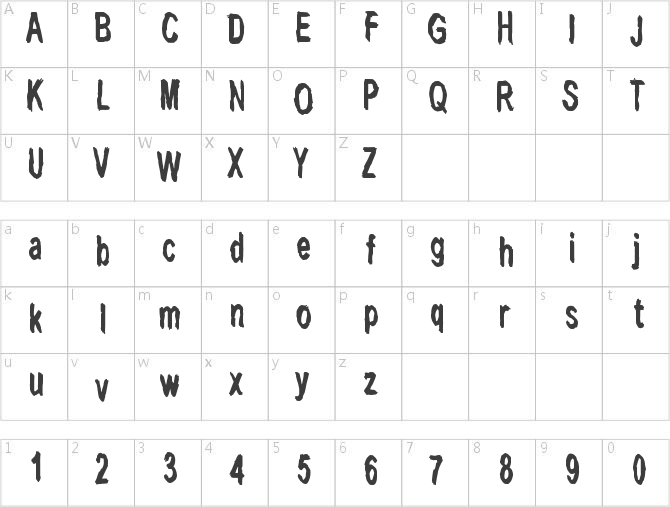
Last living souls Dark
Last living souls Dark介紹
Last living souls Dark字體字庫是一款讓人賞心悅目、百看不厭的英文字體,適合各類廣告和產品包裝設計應用,字體大小0.04MB,格式為ttf字體,上傳用戶是誠澤永信,作者/版權方為未知